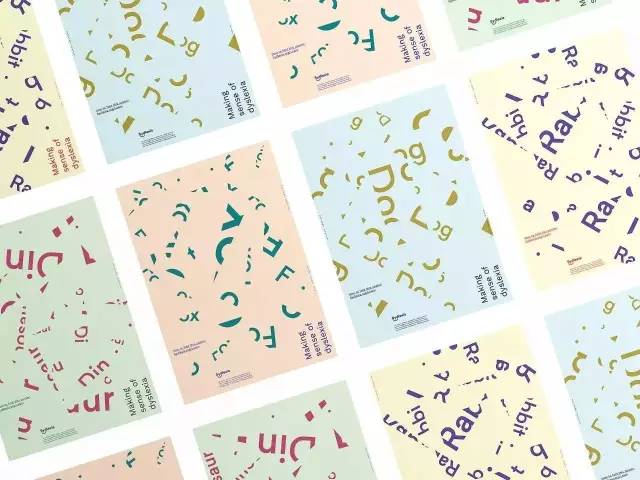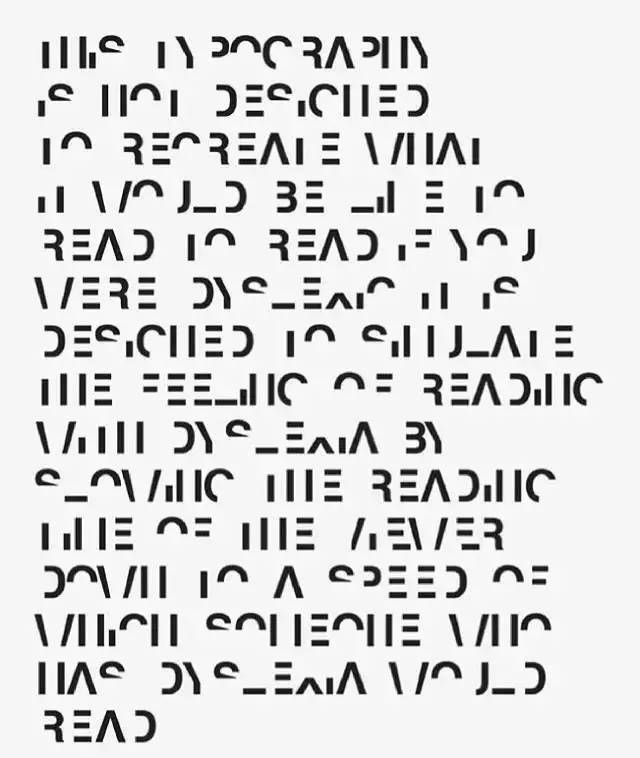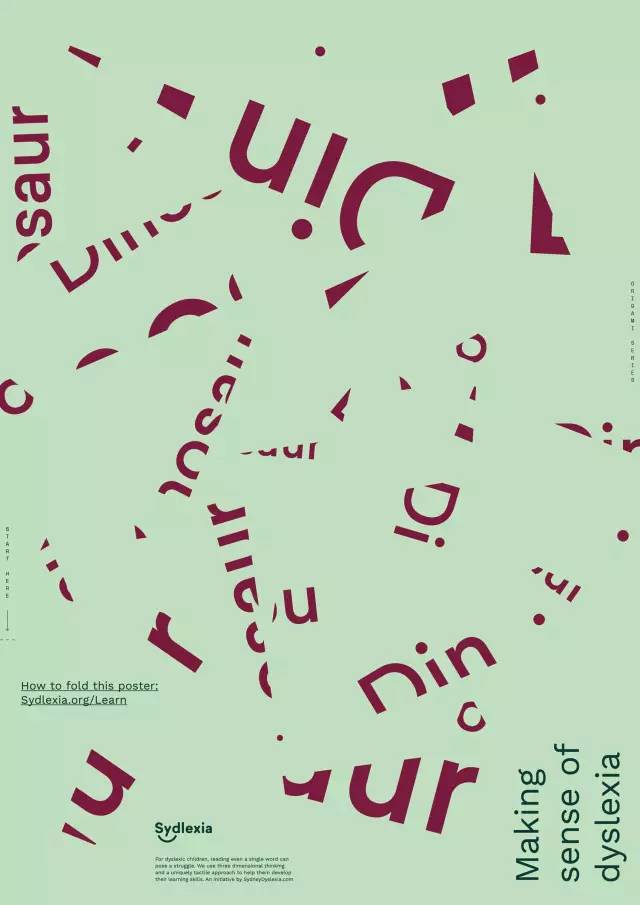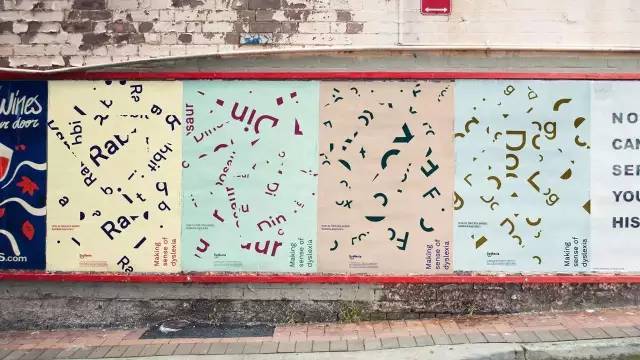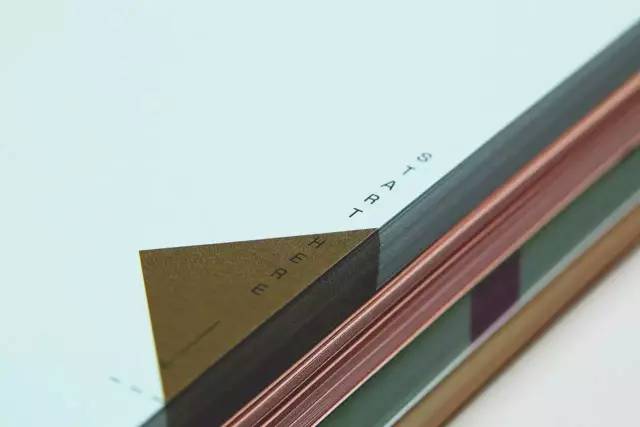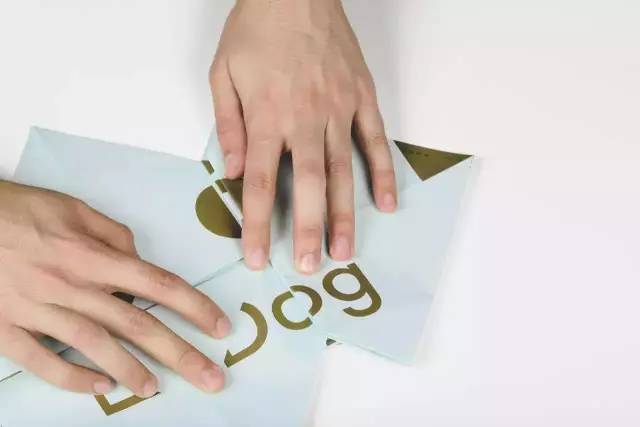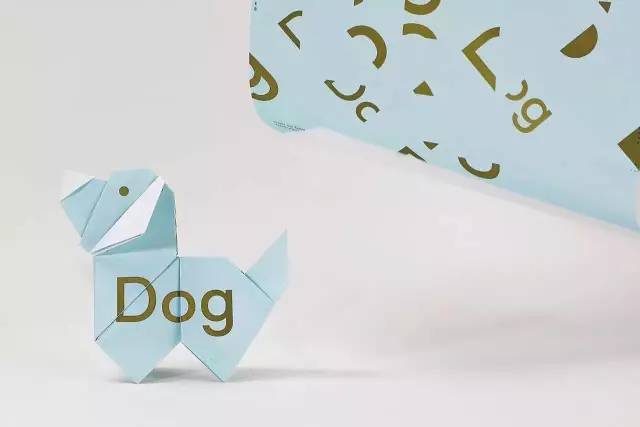
一张海报教会你什么是感同身受
读写障碍症(Dyslexia)是一种大脑综合处理视觉和听觉信息不能协调而引起的一种阅读和拼写障碍。
谈及读写障碍症很多人第一反应是火星文,一位患有读写障碍症的图形设计师在流行字体Helvetica的基础上设计并命名为Dyslexia的字体,你能读懂这段话的意思吗?
实际上他们阅读起来,文字真的在旋转跳跃不停歇。
为了让更多人了解这一病症,同时也帮助患者改善读写能力,Sydlexia公司推出了一款折纸海报,既能拿来张贴用以科普和宣传读写障碍症,又可以帮助患者通过折叠来认字。
虽然患有读写障碍的人思维方式略有不同,但在视觉、触觉等多方面的刺激下,他们更容易掌握阅读。这些海报一旦正确折叠,便会出现一个动物和它对应的名字,患者由此知道正确的单词。
回到文章开头,那张看起来像火星文一样的海报,其实是在说:
"This typography is not designed to recreate what it would be like to read if you were dyslexic it is designed to simulate the feeling of reading with dyslexia by slowing the reading time of the viewer down to a speed of which someone who has dyslexia would read."
大意即:这种特殊排版,并不是为了让你“读”出读写障碍症患者的感觉,相反,它被刻意设计成这样是为了减缓阅读时间,让人感同身受地体会读写障碍症患者可能有的阅读速度。